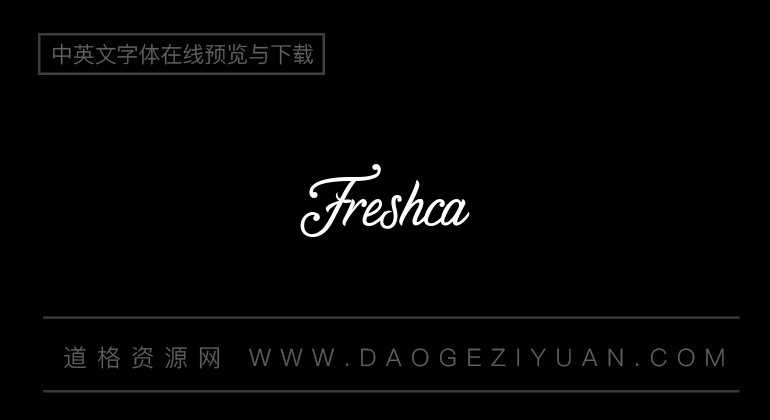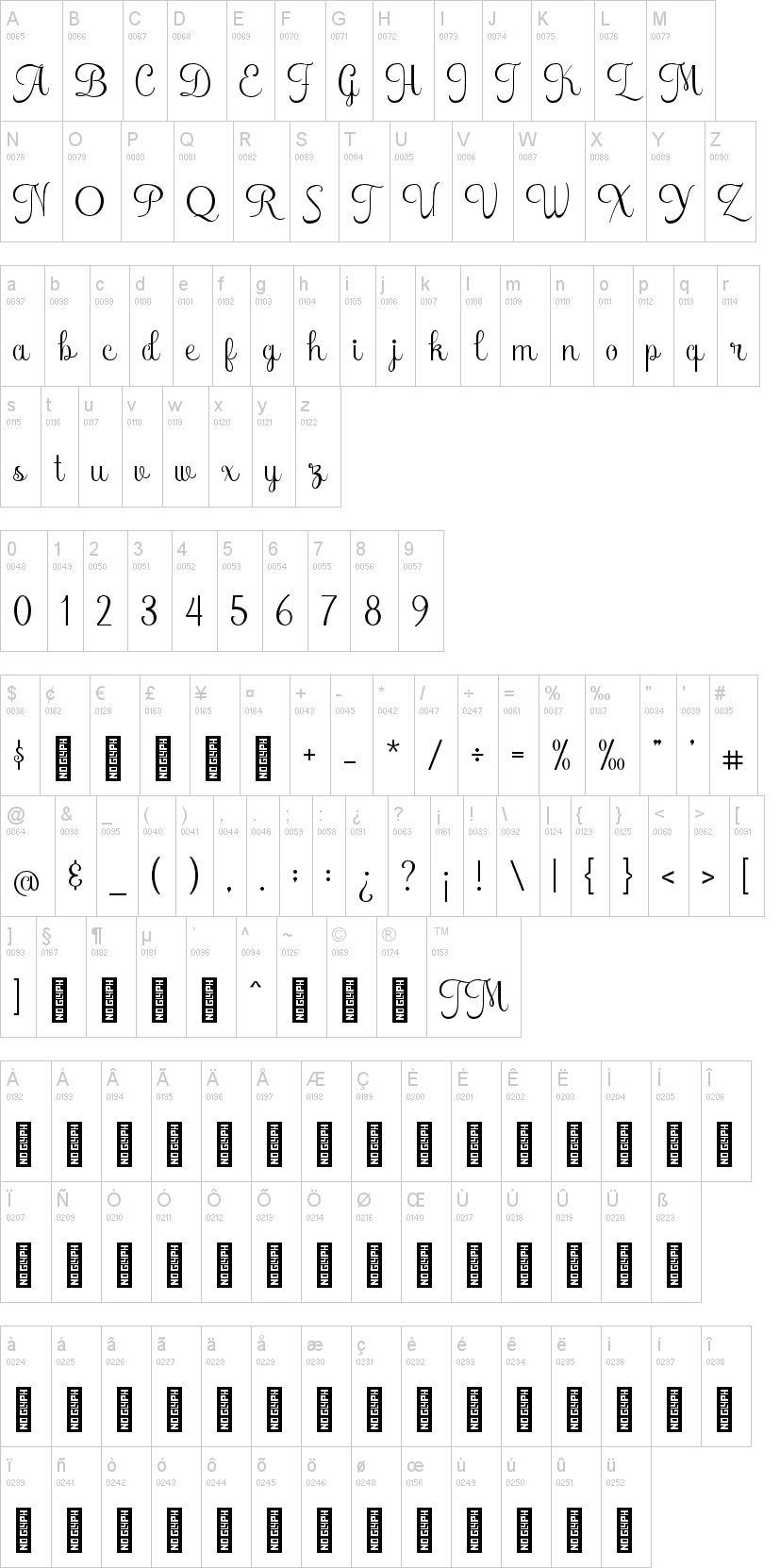
Freshca
Freshca 字体是一款简洁、时尚的线性字体,由 Fontfabric 公司设计,用于各种商业和个人项目,如标题、标签和按钮。Freshca 字体具有现代感,并且具有较高的可读性,可以在任何尺寸下都保持其外观效果。它还支持多种语言,可以满足多种不同文化的需求。
Freshca是一款非常不错的手写艺术字体,具有很好的视觉感,适合于文化类的宣传设计、商业类品牌的广告和产品包装设计以及个性化文字排版等较多场景。
Freshca字符映射图